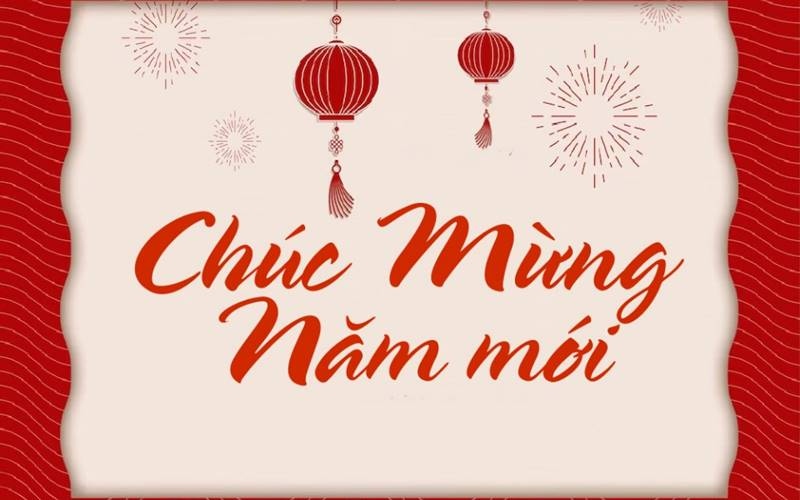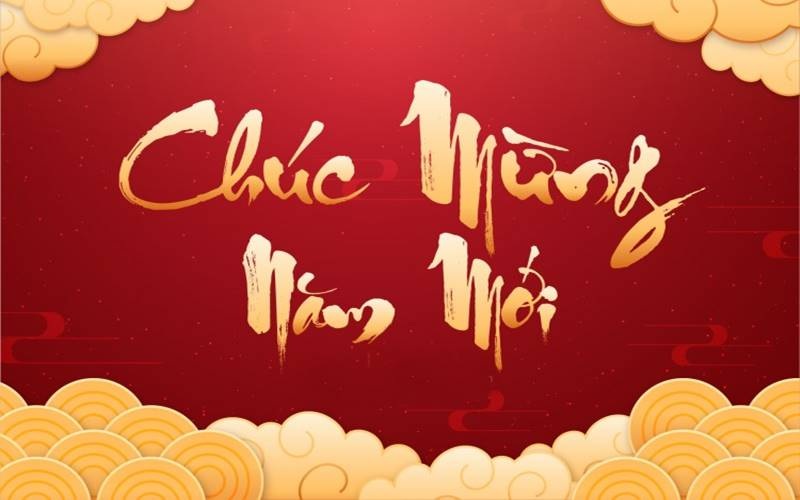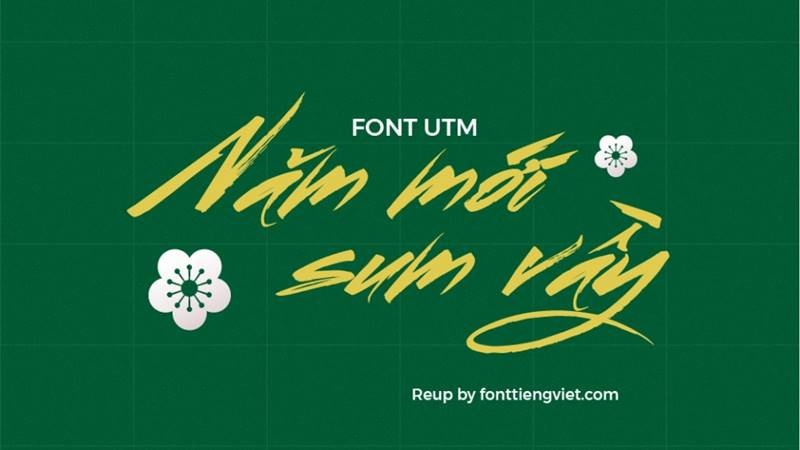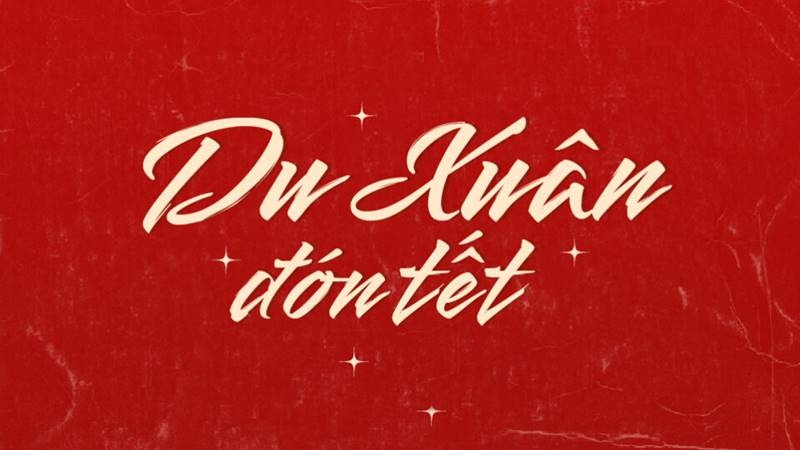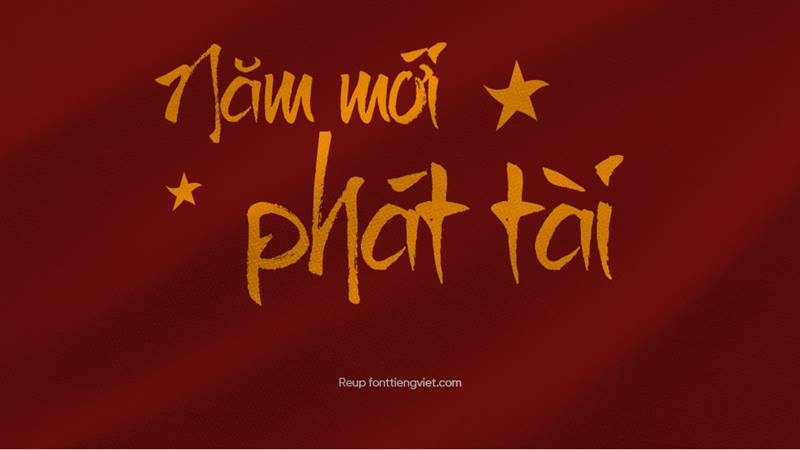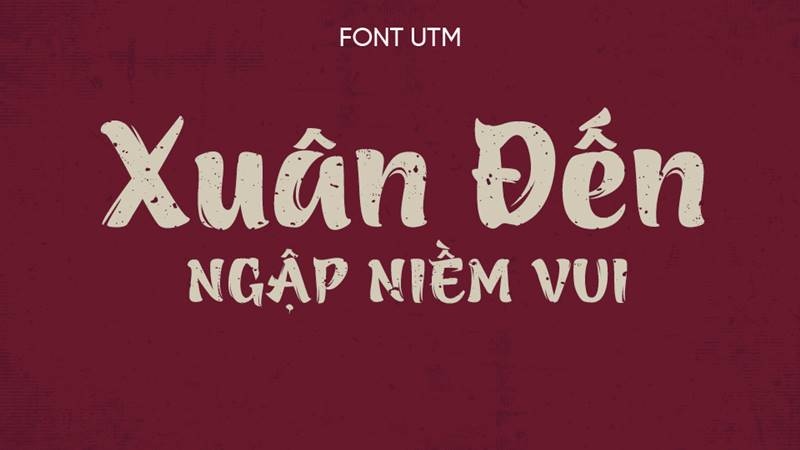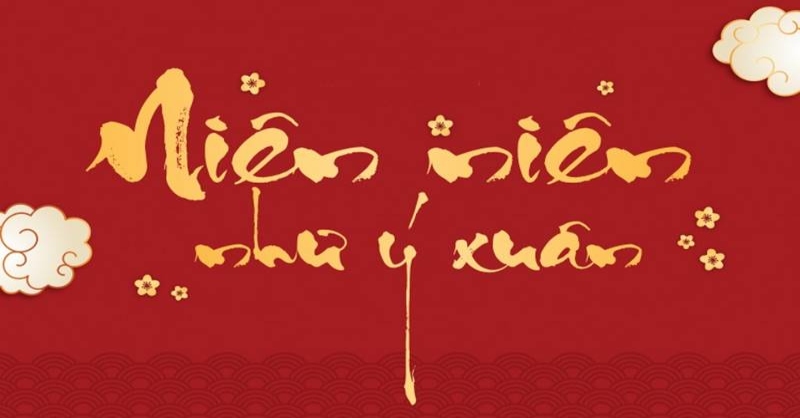
Tổng hợp font chữ thư pháp Tết đẹp, độc đáo năm 2026
Những thiết kế ngày Tết luôn trở nên ấn tượng hơn khi kết hợp cùng các font chữ thư pháp mang sắc thái truyền thống và nghệ thuật. Bài viết tổng hợp font chữ thư pháp Tết được yêu thích hiện nay, giúp bạn dễ dàng chọn phong cách phù hợp cho câu đối, banner hay thiệp chúc mừng. Hãy cùng khám phá chi tiết trong nội dung dưới đây.
Font chữ thư pháp Tết sáng tạoGợi ý các Font chữ thư pháp Tết sáng tạo, ý nghĩa
1. Các phong cách chữ thư pháp Tết phổ biến
Trong thư pháp ngày Tết, một số phong cách chữ thường được lựa chọn bởi nét đặc trưng và ý nghĩa riêng:
• Khải Thư: Kiểu chữ rõ ràng và nghiêm túc, thể hiện sự tôn kính và uy nghi, thường xuất hiện trong các câu đối Tết mang tính trang trọng
• Hành Thư: Nét viết mạnh mẽ, dứt khoát và linh hoạt, tạo cảm giác phóng khoáng và tự do, thường thấy trong thiệp chúc Tết hoặc hình ảnh chào năm mới
• Thảo Thư: Nét chữ uyển chuyển và mềm mại, đem lại cảm giác nhẹ nhàng và thanh thoát, thường được lựa chọn để viết những lời chúc Tết mang chiều sâu nghệ thuật
2. Tổng hợp font chữ thư pháp Tết đẹp
2.1 Font chữ thư pháp viết câu đối Tết
Font Smooch (Gõ tiếng Việt ) thư pháp
Font Smooch mang nét mềm mại, bay bổng giống chữ viết tay nghệ thuật. Khi được Việt hóa hoặc hỗ trợ gõ tiếng Việt, kiểu chữ tạo cảm giác thanh thoát và lãng mạn, phù hợp cho tiêu đề, câu chúc hoặc thiết kế mang hơi hướng thư pháp hiện đại. Nét chữ uốn lượn giúp tăng tính thẩm mỹ cho các ấn phẩm Tết hoặc poster trang trí.
Font Smooch (Gõ tiếng Việt ) thư phápFont chữ Smooch
Font việt hóa UTM Ông Đồ Già
Phiên bản Ông Đồ Già tái hiện chất cổ điển của bút lông truyền thống, với nét chắc khỏe và giàu chiều sâu. Khi sử dụng trong câu đối hay tranh chữ Tết, font gợi không khí nghiêm trang và đậm màu văn hóa xưa.
Phiên bản Ông Đồ Già tái hiện chất cổ điểnFont việt hóa UTM Ông Đồ Già
Font việt hóa UTM Ông Đồ Trẻ
Font việt hóa UTM Ông Đồ Trẻ giữ tinh thần thư pháp nhưng được làm mềm và linh hoạt hơn, tạo cảm giác tươi mới và dễ tiếp cận. Font phù hợp với các thiết kế Tết mang phong cách trẻ trung, kết hợp giữa truyền thống và hiện đại.
Font UTM Ông Đồ Trẻ giữ tinh thần thư phápFont việt hóa UTM Ông Đồ Trẻ
Font việt hóa UTM Brushtip-C
Brushtip-C gây ấn tượng bằng nét cọ mạnh, dứt khoát và giàu năng lượng, gần với phong cách thư pháp hiện đại Á Đông. Font giúp tiêu đề, poster hoặc banner Tết trở nên nổi bật, mạnh mẽ và cuốn hút.
Font việt hóa UTM Brushtip-C với nét cọ mạnhFont việt hóa UTM Brushtip-C
2.2 Font chữ thư pháp cách điệu
Font Việt hóa UTM Azuki
UTM Azuki mang vẻ mềm mại và duyên dáng với những đường cong nhẹ, gợi cảm giác tươi sáng và thân thiện. Font tạo cảm giác ấm áp, rất hợp cho các thiết kế Tết thiên về sự dễ thương, nhẹ nhàng hoặc phong cách trẻ trung.
Font UTM Azuki mang vẻ mềm mại Font Việt hóa UTM Azuki
Font Việt hóa UTM Spring
UTM Spring tạo ấn tượng bằng nét chữ thanh thoát và tràn đầy sức sống, mô phỏng cảm giác mùa xuân mới mẻ. Khi đưa vào poster hoặc thiệp Tết, font đem lại cảm giác vui tươi và sinh động, phù hợp các thông điệp chào năm mới rộn ràng.
UTM Spring dạng font việt hóaFont Việt hóa UTM Spring
Font chữ thư pháp cách điệu
Dạng font này dựa trên thư pháp truyền thống nhưng được biến tấu hình dáng chữ để tạo cảm giác hiện đại và phá cách. Nhờ sự sáng tạo trong nét bút, font thường mang sắc thái nghệ thuật mạnh, giúp tiêu đề hoặc câu chúc Tết trở nên độc đáo và nổi bật.
Dạng Font chữ thư pháp cách điệu